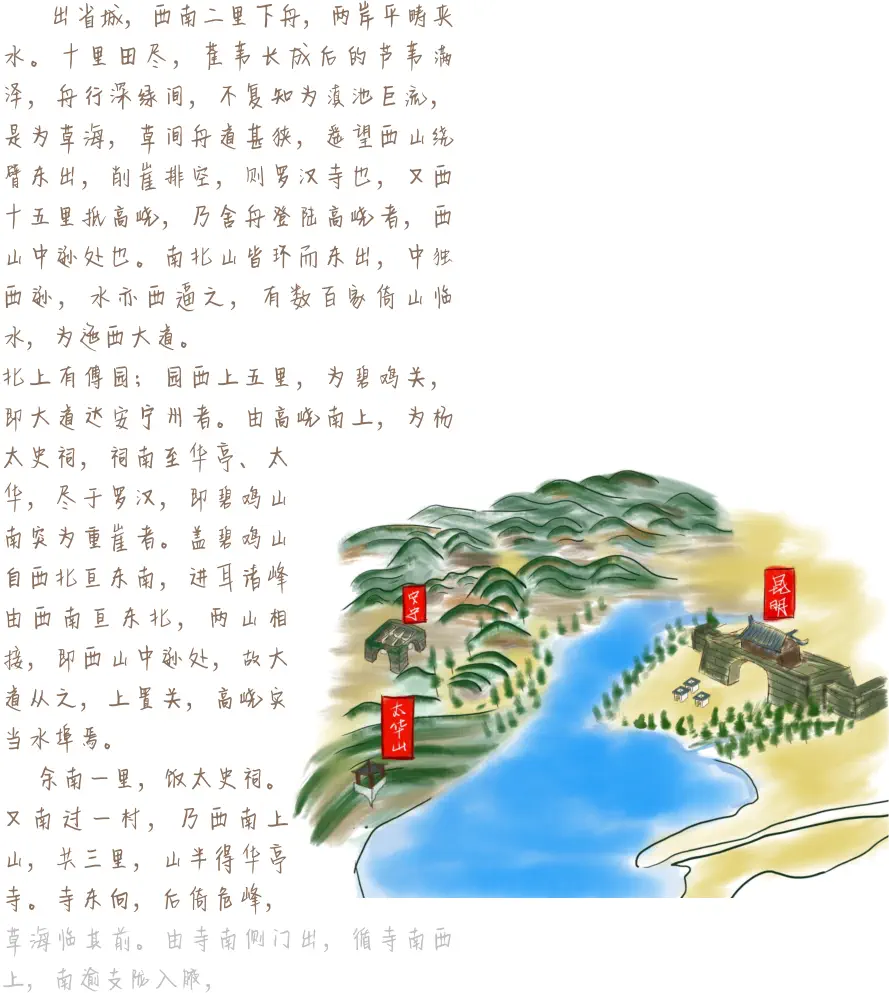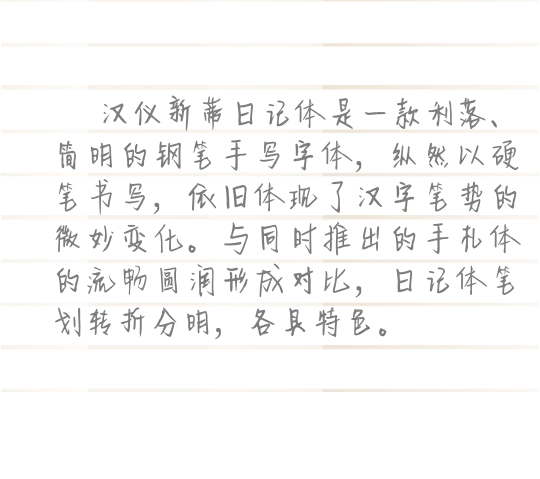
汉仪新蒂日记体 Hanyi Senty diary Handwriting 出省城,西南二里下舟,两岸平畴夹水。十里田尽,萑苇长成后的芦苇满泽,舟行深绿间,不复知为滇池巨流,是为草海,草间舟道甚狭,遥望西山绕臂东出,削崖排空,则罗汉寺也,又西十五里抵高峣,乃舍舟登陆高峣者,西山中逊处也。南北山皆环而东出,中独西逊,水亦西逼之,有数百家倚山临水,为迤西大道。 北上有傅园;园西上五里,为碧鸡关,即大道达安宁州者。由高峣南上,为杨太史祠,祠南至华亭、太华,尽于罗汉,即碧鸡山南突为重崖者。盖碧鸡山自西北亘东南,进耳诸峰由西南亘东北,两山相接,即西山中逊处,故大道从之,上置关,高峣实当水埠焉。     余南一里,饭太史祠。又南过一村,乃西南上山,共三里,山半得华亭寺。寺东向,后倚危峰,草海临其前。由寺南侧门出,循寺南西上,南逾支陇入腋,
汉仪新蒂日记体是一款利落、简明的钢笔手写字体,纵然以硬笔书写,依旧体现了汉字笔势的微妙变化。与同时推出的手札体的流畅圆润形成对比,日记体笔划转折分明,各具特色。